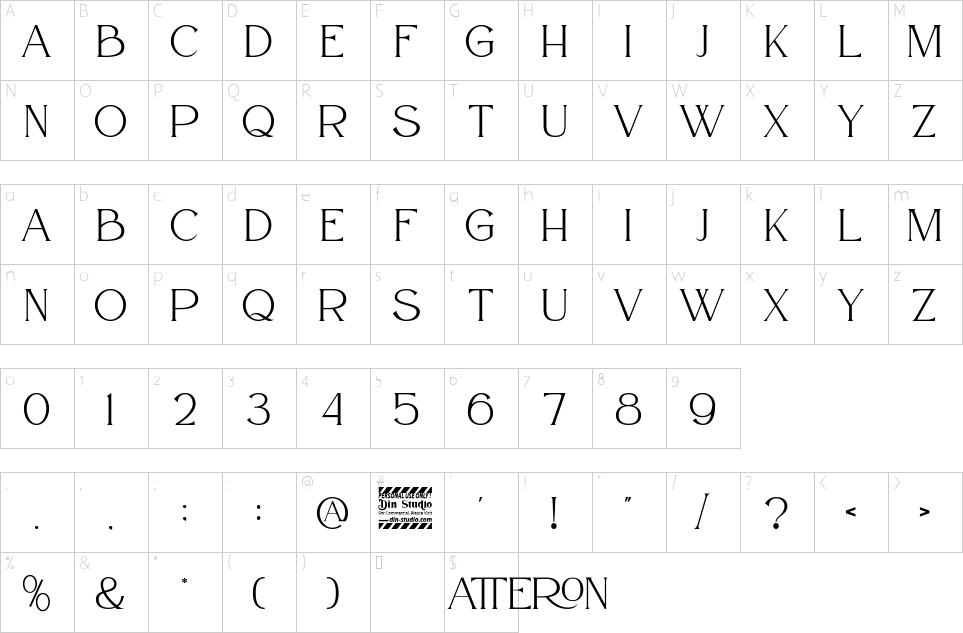
Atteron Font – Fonte Grátis
Atteron Font
Descubra a beleza do Atteron font, uma opção elegante e versátil para seus projetos digitais. Desenvolvida pelo designer Donis Miftahudin, esta fonte oferece um toque sofisticado em qualquer layout. Com seu design cuidadosamente elaborado, o Atteron pode complementar perfeitamente os seus designs para criações web, gráficos ou qualquer outro tipo de projeto. Esta fonte está disponível tanto para sistemas Windows quanto para Mac, tornando-a acessível para todos. Até agora, ela foi descarregada 534 vezes, evidenciando seu valor e popularidade entre os designers. Inclua o Atteron em seus projetos para adicionar uma camada de profundidade e classe à sua arte digital.